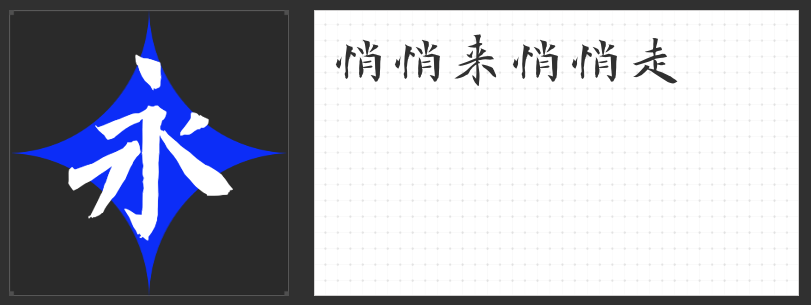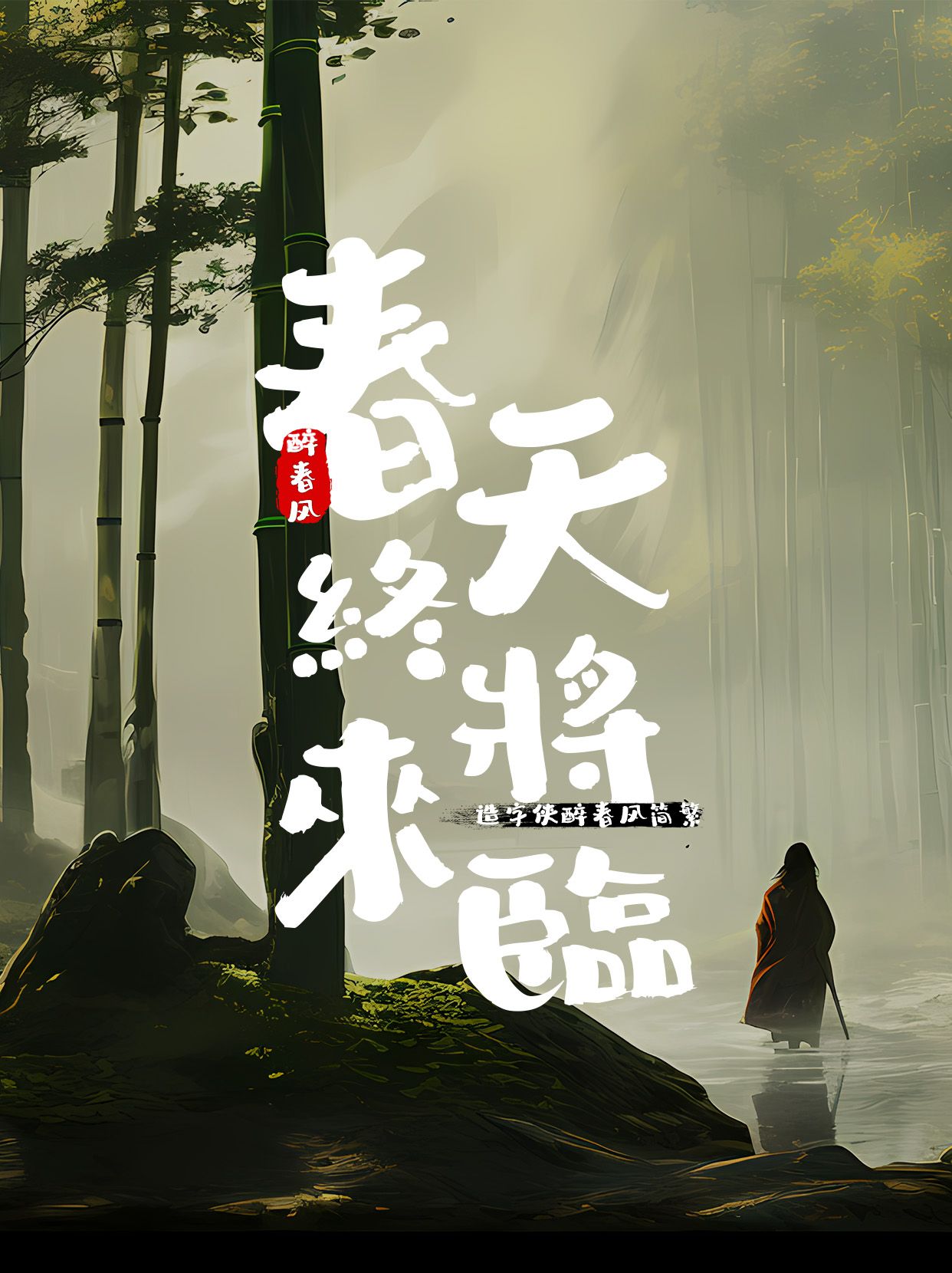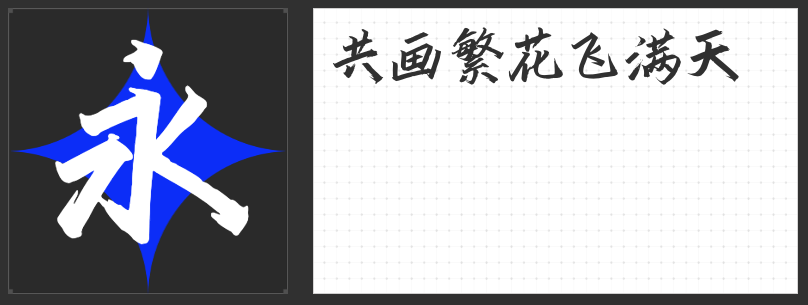
古风韵味,字里行间——探索古风字体之美
在浩瀚的中华文化底蕴中,古风字体犹如穿越时空的信使,以其独特的韵味与美感,承载着千年的历史与文化的精髓。今日,便让我们一同漫步于这古韵悠长的字体世界,探寻几款不可多得的古风字体推荐。
造字侠今朝醉简,其字形简约而不失韵味,完美融合了古典美学与现代审美。在古风海报、诗词歌赋、插画配文等设计中,造字侠今朝醉简以其独特的风格,营造出一种朦胧而雅致的氛围,让人仿佛置身于古色古香的场景中,沉醉于那份超脱世俗的宁静与美好。无论是传统文化的传承还是现代设计的创新,造字侠今朝醉简都是不可多得的选择。
云书法家韩进水魏碑简繁承袭魏碑之雄浑古朴,笔画结合间展现独特韵味,每一笔一划都仿佛历史的低语,诉说着千年故事。在古风海报、书籍封面、诗词题字等设计中,云书法家韩进水魏碑简繁能够瞬间营造出浓厚的历史文化氛围,让观者仿佛穿越时空,感受那份来自远古的庄重与雅致。
造字侠磅礴简繁气势磅礴,每一笔都蕴含着山河的壮阔与历史的深邃。在古风海报、历史长卷或宫廷剧字幕中,造字侠磅礴简繁以其独特的力量感与古典美,勾勒出一幅幅震撼人心的画面,让人仿佛置身于那个辉煌的时代。选择造字侠磅礴简繁,为古风设计增添一抹不可多得的雄浑之气。
“造字侠醉春风简繁 苍劲”虽非严格意义上的古风字体,但其流畅自然、行云流水般的书写风格,与古代文人墨客的书法意趣相契合,透露出一种超脱世俗、洒脱不羁的韵味。在书写诗词、散文时,使用造字侠醉春风简繁 苍劲能增添几分文人雅士的风骨与情怀。
古风字体,是时间的低语,是文化的传承。每一款字体背后,都藏着一段段历史的故事,一段段文化的记忆。让我们在书写与设计中,巧妙地运用这些古风字体,让传统文化之美在现代社会中绽放新的光彩。